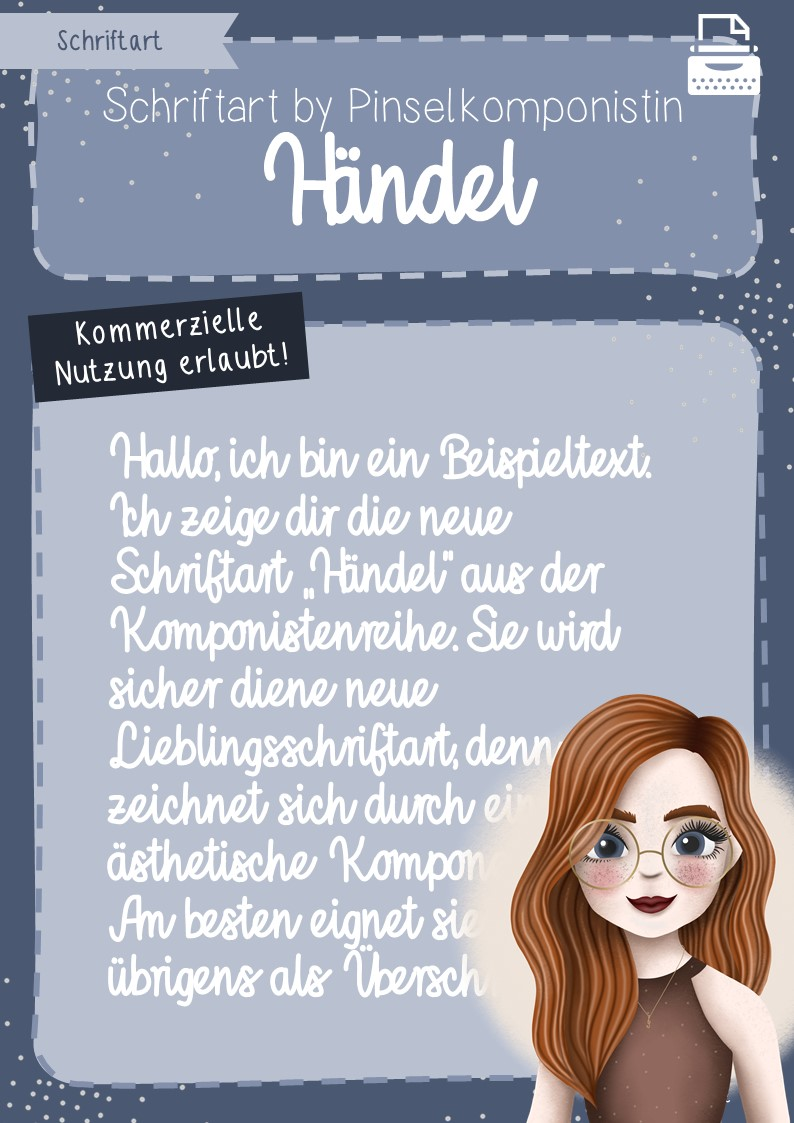
Hier ist die nächste Schriftart für die Komponistenreihe! "Händel" ist eine liebevoll erstellte Schriftart, die dekorativ ziemlich was hermacht. Sie zeichnet sich durch eine Mischung aus ästhetischer Schnörkelschrift und Handschrift aus.
Schriftart: Händel by Pinselkomponistin